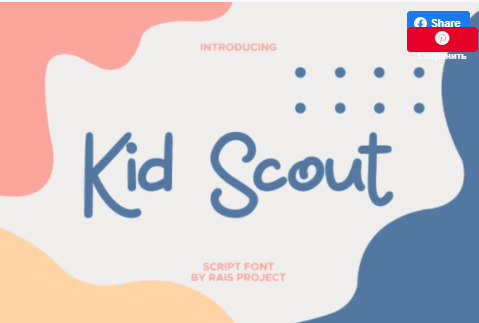
Kid Scout Font
Kid Scout - это простой рукописный шрифт, который можно использовать для всех цитат на классной доске или учебных материалов! Его аутентичный внешний вид добавит индивидуальности и реалистичности вашему дизайну.